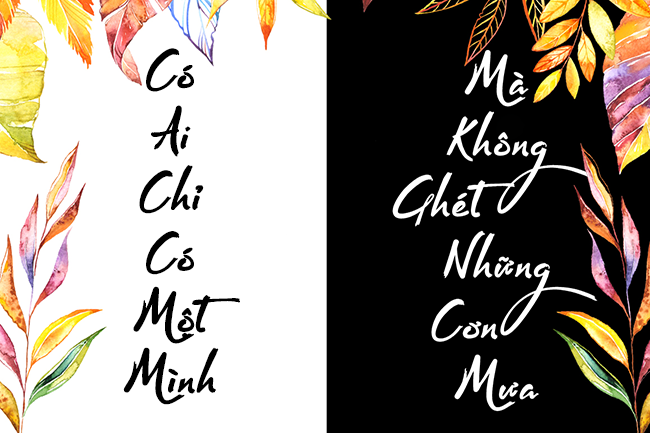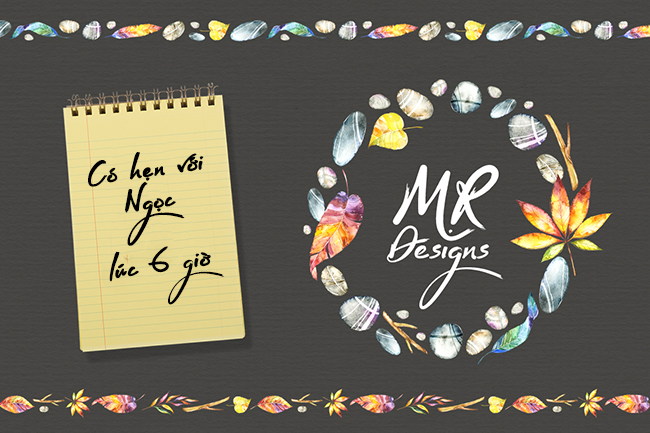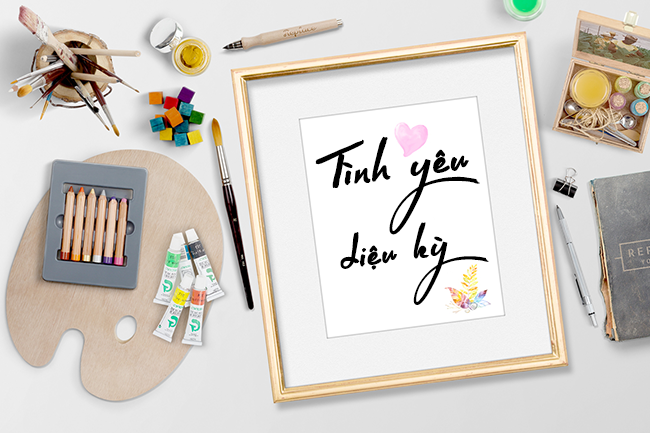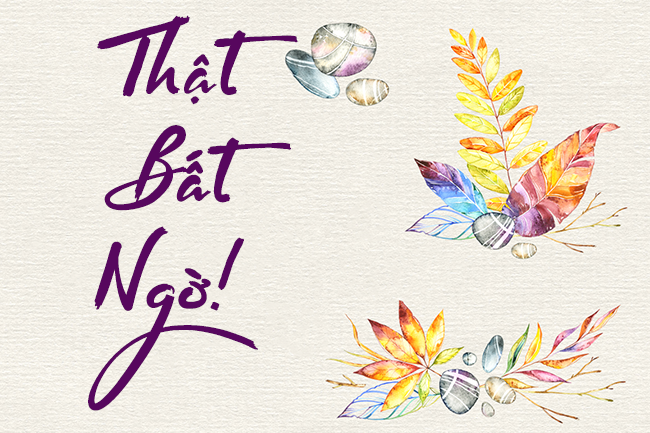
Artful Beauty là một font brush mượt mà, sắc nét và rõ ràng, có thể sử dụng cho hầu như mọi mục đích. Font dễ đọc với tất cả mọi người, mang cảm giác chữ viết tay tự nhiên nhưng vẫn toát lên sự thanh lịch. Đây là lựa chọn lý tưởng cho các dự án cần hiệu ứng vẽ tay đang rất được ưa chuộng. Artful Beauty được phát triển dựa trên một font trong bộ Designer’s Kit mang tên Regular Rolf, với nét chữ dày hơn, hiệu ứng cọ vẽ rõ ràng và phong cách calligraphy nổi bật hơn.
Nhà thiết kế: Joanne Hewitt